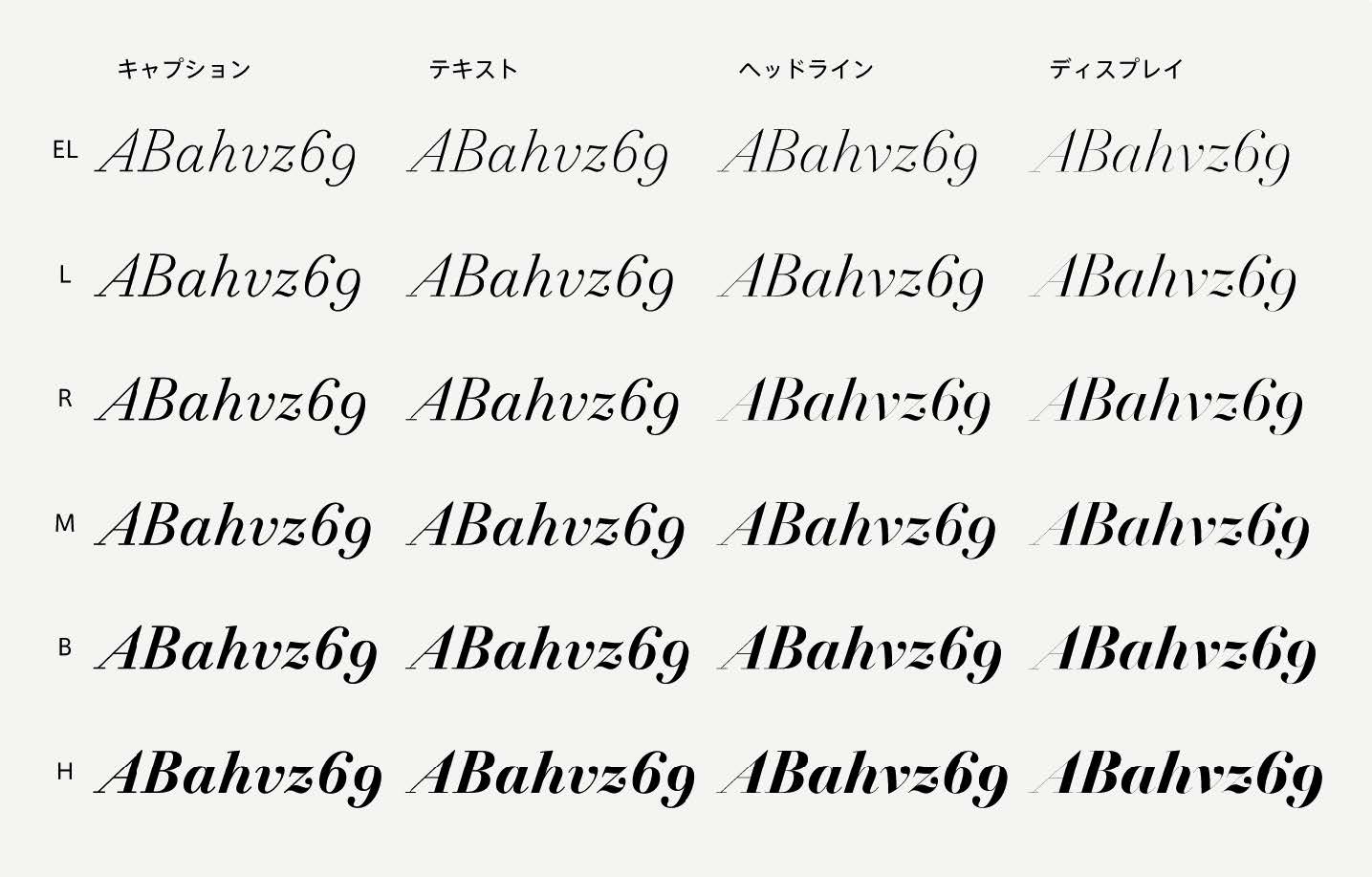
タイププロジェクト、都市フォントの「濱明朝」シリーズに欧文イタリック体「Hama Mincho Italic」を追加
各バリエーションで文字の骨格を変え、合字やオールドスタイル数字を追加
タイププロジェクト株式会社(東京都練馬区 代表取締役社長 鈴木 功、以下タイププロジェクト)は、都市フォントプロジェクトのひとつである「濱明朝」シリーズとして、欧文イタリック体「Hama MinchoItalic(濱明朝イタリック)」の発売開始を発表しました。
「Hama Mincho Italic」は、全体に流線的な形状を採用し、横浜の風や波を想起させる雰囲気を持たせています。正体のデザインがハイコントラストですっきりとした漢字に近いのに対し、イタリック体では筆脈を残した柔らかい雰囲気を持つ仮名に合わせた印象に仕上げています。また、ウエイトごとの特徴は正体と調和させつつ、いくつかの文字の形状やプロポーションを意図的に変えています。
タイププロジェクトの代表取締役 鈴木 功は、「濱明朝の魅力をさらに引き出す欧文イタリック体を発表できることをとても嬉しく思っています。Hama Mincho Italicでは、バリエーションごとにふっくらとしたモダンローマン系のデザインや、クラシカルなイタリックの骨格を採用し、小文字の字形を変えていますので、スピード感の演出や可読性の追求など幅広くご利用いただけます。今まで以上に多くの場面で濱明朝をご使用いただくことを楽しみにしています」と述べています。
Hama Mincho Italicでは、合字やプロポーショナル数字、オールドスタイル数字を追加しています。装飾的なデザインの「st」「fy」などの合字では、波の形を思わせるデザインを採用しています。また、小文字の「v」と「w」の字形をバリエーションによって変えています。
■ Hama Mincho Italic
2010年にタイププロジェクトが発表した都市フォント構想は、都市独自のフォントをコミュニケーションツールとして活用することで、都市のアイデンティティを強化しようという試みです。2017年7月には横浜をイメージした「濱明朝」、2020年3月には名古屋をイメージした「金シャチフォント 姫」、2020年7月には「東京シティフォント」の発売を開始しています。濱明朝は、大佛次郎記念館のサインや、天野和俊デザイン事務所が最優秀賞を受賞した横浜市中区馬車道商店街協同組合の150年記念ロゴタイプに採用されています。